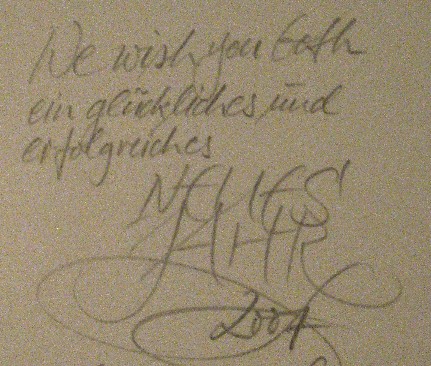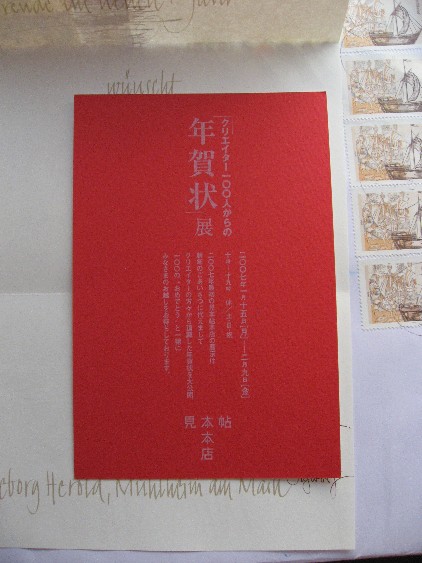
巨匠の手書き
お年玉付年賀状の当選発表も終わり、
喜んだ人、惜しい〜と呟いた人…と皆様
いかがでしたか?
さて、見本帖のギャラリーでは今
「クリエイター100人からの年賀状」展が
開催されています。
ちなみにこのDMはリバーシブルマーメイドで宛名側がスノーホワイト、案内側が赤なんです。リバーシブルマーメイドのボードは好きで使ったことがあるのですが、こんな薄いのもあるんですねぇ〜。お正月にぴったりの紙ですよねぇ!
ギャラリーへ足を運ぶとそこには、デザイナーさん達のステキな年賀状がずらり!
巨匠たちの年賀状もそこここに…。紙に凝っている方…しかしデザインは意外とシンプル。
そのシンプルな世界が印象に残る…とやはりお仕事ができる方達なんですねぇ〜。
見ていてため息がでました。クリエーターの方達は、もちろん見本帖さん宛にご挨拶してるの
ですが、何だか見ているこちらにも「おめでとう」と言ってくださっているみたいで…ちょっと
嬉しいかも(勘違い…勘違い…)!
何よりも一番感動したのは、宛名のほとんどが手書きだということでした。
一般peopleの間では、宛名も印刷が多くなって…ちょっと寂しい気がしているのですが、
こんなにお忙しい方達が手書き文字を残しているのです!
福田繁雄さんとか松永真さんとかがですよ〜!すご〜い!感激〜!
巨匠というものは、その個人的に
書かれる文字もイキイキしていて本当にステキです。いつでもどこでもこんな文字が書けるようになったら…。憧れですよねぇ〜。